対談「1文字から1万文字までの話」(色部義昭×鈴木功)から
文字とデザインの背景にあるもの
「クリエイションギャラリーG8」の30周年を記念したトークイベント「30話」は、同ギャラリーにゆかりのある30人が、それぞれの対談相手を指名する形式で開催中です。2016年2月25日の回には、日本デザインセンターの色部義昭氏からタイププロジェクトの鈴木功をご指名いただき、「1文字から1万文字までの話」と題した対談が行われました。そこから、主に鈴木の発言を、いくつかピックアップしてご紹介します。
色部:ふだん鈴木さんとお話ししていると、非常に考え方が近いなあと感じることがあります。たとえば、文字を作るときに、単純にどんな文字を作りたいというのではなくて、その文字が実際に使われる背景を見つめて、そこにどういうものが必要になるかという部分から考え始めるとか。その一方で、僕の場合、グラフィックデザインという、どちらかといえば期間の短いものを考えていくことが多いのですが、鈴木さんの場合、ずっと使われていく書体、いろんな人が思いもよらないような使い方をしたりする文字というものをデザインをされている。それはグラフィック的な仕事でありながら、むしろプロダクトデザインに近いなという感覚があって、そのあたりの話を聞いていると、個人的にとても面白いので、今日は対談という形式ですが、鈴木さんの話が聞きたいなと思ってお招きしました。どうぞよろしくお願いします。
鈴木:色部さん、ありがとうございます。今回の対談については、色部さんと打ち合わせを進めるなかで、ちょっと変わった趣向でやってみようということになりました。色部さんと僕が順番にそれぞれの作品をプレゼンテーションするのではなく、文字が、1文字から10文字、100文字、1000文字と増えていくときに、書体デザインあるいはグラフィックデザインにおいて、どういうふうに考え方が変わっていくのか、という点を軸にしてお話ししていきたいと思います。
「まるはち」と金シャチ黒字
鈴木:書体デザインでは、1万文字とかを作るわけですが、最初はたった1文字からインスピレーションを得るということもあります。いまスクリーンに出ているのは「まるはち」と呼ばれる名古屋市の市章で、名古屋の人にとっては見慣れたマークなんですが、さかのぼると江戸時代の尾張徳川の合い印として使われていたものです。
僕は名古屋生まれで、小さい頃から「まるはち」が目になじんでいます。この文字の、ちょっと専門的な言葉になりますが、筆法、筆遣いを展開したのが、ご覧の「金シャチ黒字」という書体の「金」という字です。僕はふだん青の水性ペンでいきなり文字を描いていくのですが、今回は黒々とした文字だったので、途中で黒いペンに切り替えました。「金シャチ黒字」は、2010年くらいに作り始めた書体で、まだ完成していません。
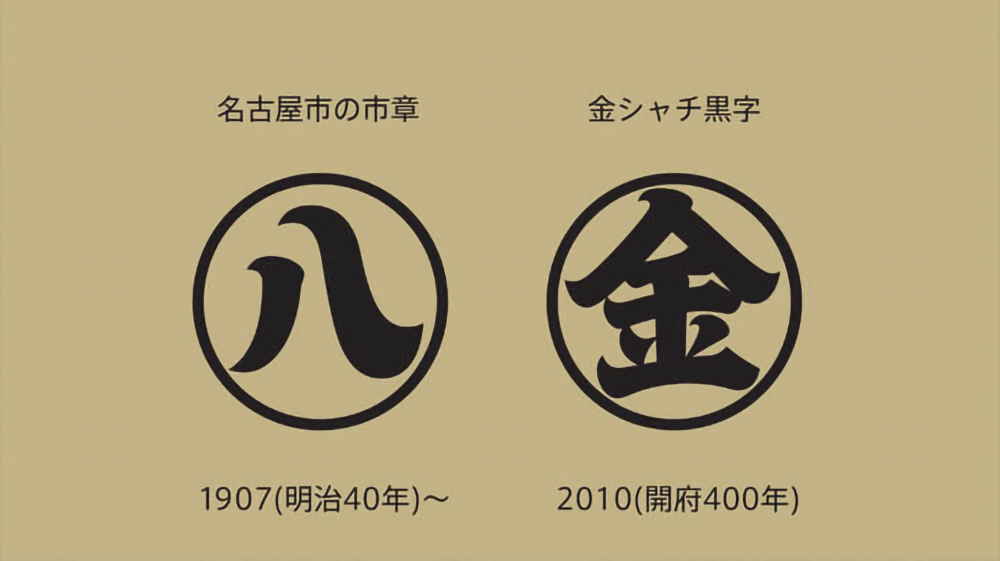
コーポレートスローガンのための文字
鈴木:ロゴデザインでは、数文字をひとかたまりとして捉えます。ご覧いただいているのは、2005年くらいにPOLAから依頼を受けて作ったコーポレートスローガンのための文字です。その後5年間くらい、テレビCMなどで使われました。書体というのは世に出るまでに長い時間がかかります。僕の手元で眠っている試作の書体がたくさんあって、これも、そのひとつでした。POLAのプロジェクトの4年前の試作、そしてそこからさらに3年ほど前の試作が存在するのですが、段階を経るごとに、より洗練された印象になるようチューニングしています。
この文字は、書体の様式でいうと宋朝体の流れを汲むものです。宋朝体は中国の宋の時代を起源とする書体ですが、そこからさらに、顔真卿という唐代の書家にまでさかのぼることができます。ひとつの書体が、切れ目なくつながっていくわけです。僕は書体を作るときに、そこに書体の歴史を重ね合わせたいなあと思っています。
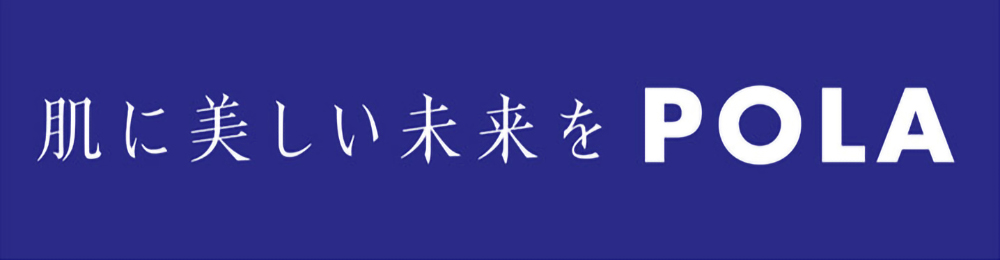
東京の街区表示板のための文字
鈴木:東京の新しい街区表示板を提案したいんだという思いを色部さんから聞いて、タイププロジェクトは、東京シティフォントを提供するという形で協力しました。現在日本で、サインシステム用に特化したフォントというのは非常に少なくて、無難な書体が使われていることが多いんです。電車を待っているときなど、僕は必ず案内表示を見るんですけど、単に読みやすいだけでなく、もう少し文字に表情があってもいいのになと、いつも思っています。
色部さんのデザインされた街区表示板では、大小の文字が混在していますが、同じ太さの文字を小さいサイズで使うと、見る人は、細く、弱く感じます。だから、この東京シティフォントには、大きく使うためのものと、小さく使うためのものと、2つあるんです。小さく使うほうが「スモール」で、ちょっと太くしてあります。さらに大きく使う「ラージ」のほうが、先端部を細く、抑揚を大きくしているんですね。つまり、大きくしたときに、表情がより豊かになるということなんです。
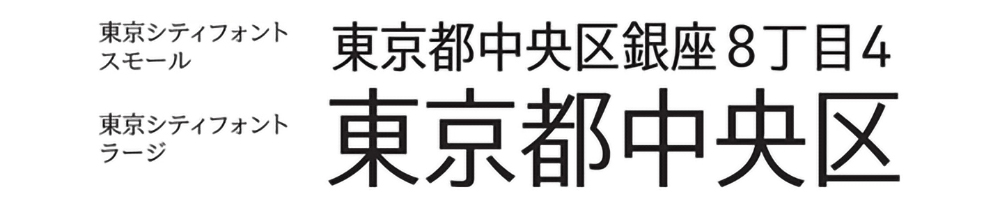
色部:それって、言われなければ気がつかないことですよね。むしろ上手にやればやるほど誰からも気づいてもらえないっていう、不思議な状況ですよね。
鈴木:なので、このような場で、お話しさせてもらっています(笑)。
テキストを組むための書体、AXIS FontとTP明朝
鈴木:AXIS Font は、「AXIS」というプロダクト系のデザイン雑誌のために開発されたフォントです。それまで「AXIS」誌で使われていたのは新ゴシックという書体でした。当時の僕が思っていたのは、もっと風通しのいいサンセリフのフォントがあったらいいんじゃないのかというものでした。サンセリフは、線だけで構成された書体ですが、それでも、たとえば曲線の質の違いだけで、印象はまったく変わってくる。これが、書体デザインの醍醐味のひとつです。
TP 明朝は、2年前に発表した明朝体です。これまで明朝体の主な舞台は、紙で、縦組みでした。これからのフォントの使われ方としては、デジタル機器のディスプレイで、横組みという機会が多いのではないか。そこではどんな明朝体が求められるのか、というのがTP明朝のチャレンジです。なので、デザインの方針は横組みに特化しています。これまで書体デザイナーが割り切れなかった部分を、本当に振り切って作りました。AXIS Fontには字幅の軸がありますが、TP明朝にはコントラストという軸があります。デジタルの世界では、環境によっては細い横画が飛んでしまうので明朝体が使いづらいという状況がありました。それはもったいないですよねということで、いまの時代に明朝体の新しい出番を作りたいというのが、この書体の大きな狙いです。
色部:AXIS Fontのコンデンスが出たときは衝撃を受けましたが、TP明朝の「骨格を変えずにコントラストを変える」というアプローチにもびっくりしました。目の前にある形をどうしようかということではなくて、背景にある条件を追い込んでいくことでデザインの可能性を見出していく、そこによろこびを見出しているところが一緒だなと感じました。